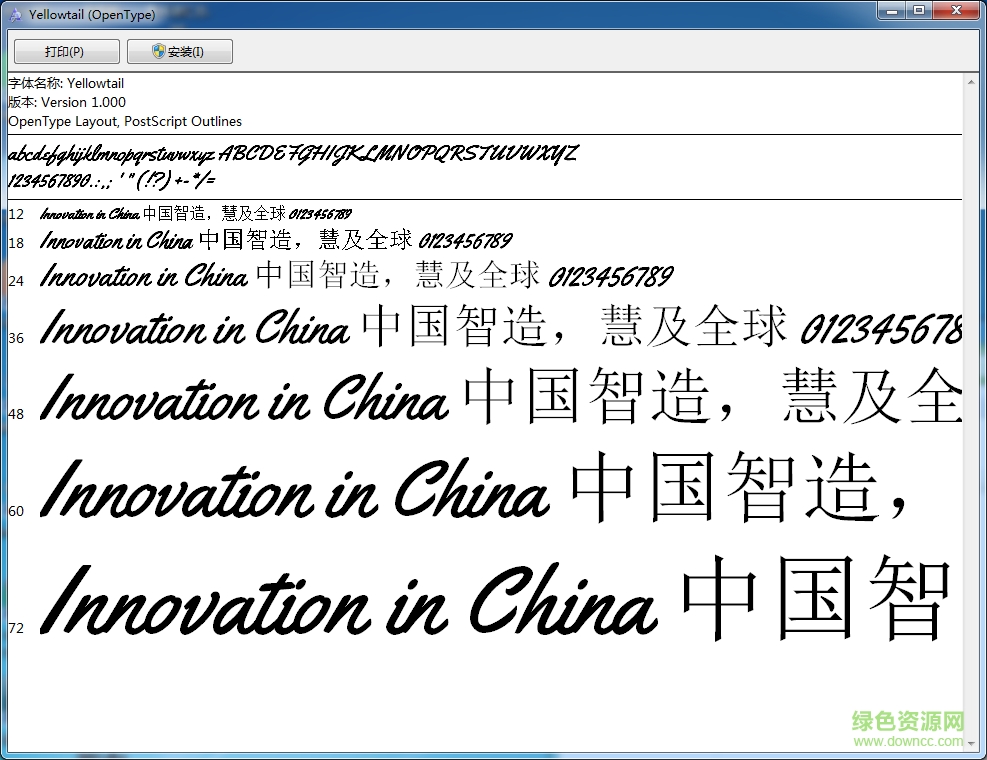
Yellowtail字體是一款非常有個(gè)性的電腦字體,字體傾斜纖細(xì)極具美感,使用流暢應(yīng)用廣泛,可直接導(dǎo)入多款設(shè)計(jì)軟件中使用。快來(lái)綠色資源網(wǎng)下載體驗(yàn)吧!
Yellowtail字體是一款很不錯(cuò)的電腦字體,寫出來(lái)的字是很好看的,而且實(shí)用性強(qiáng),可以用于很多方面。